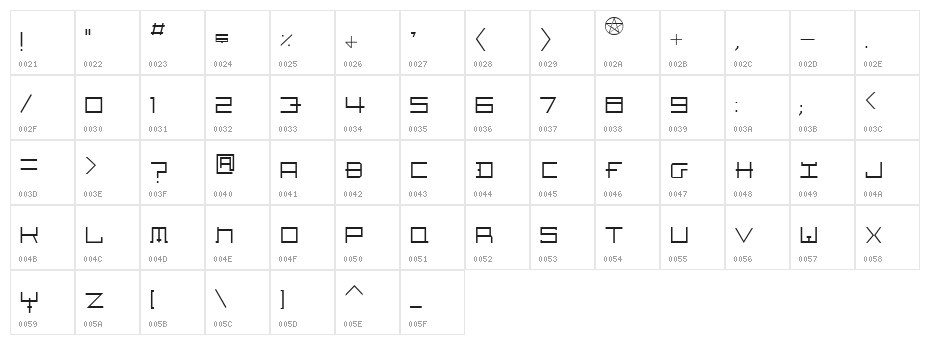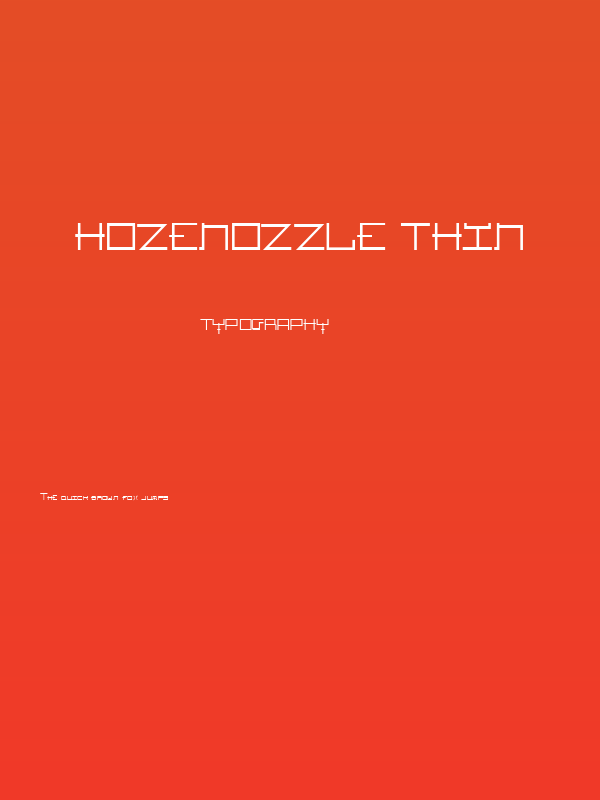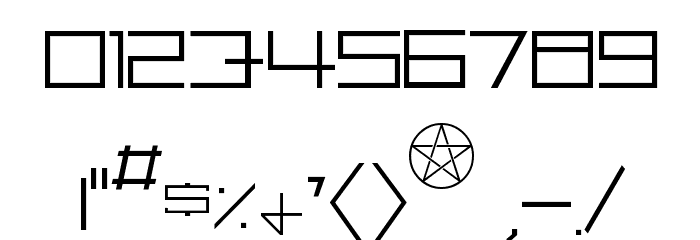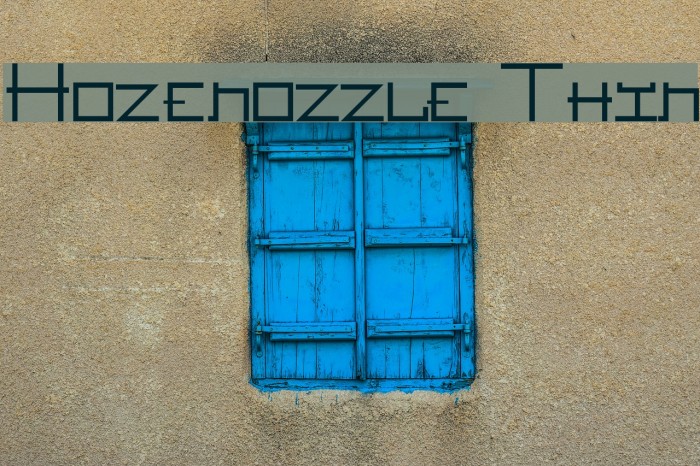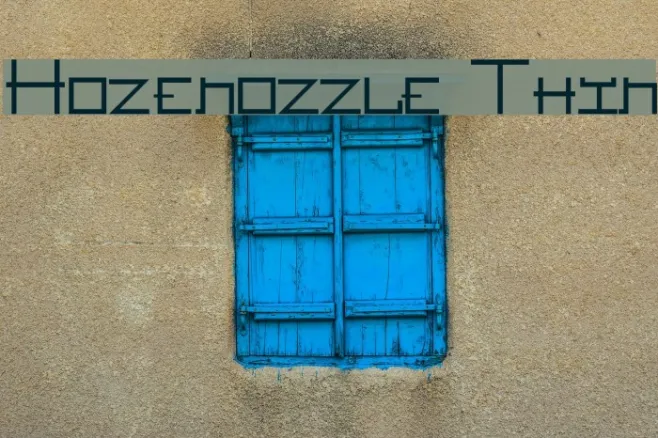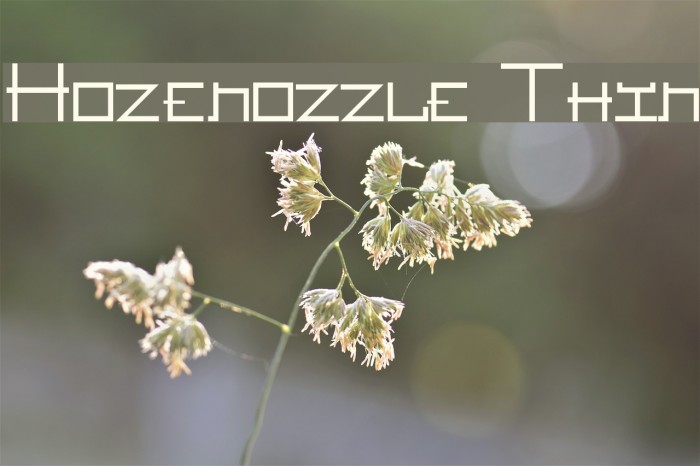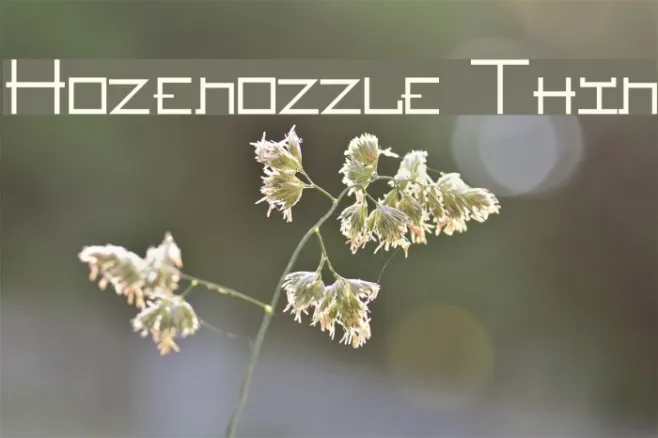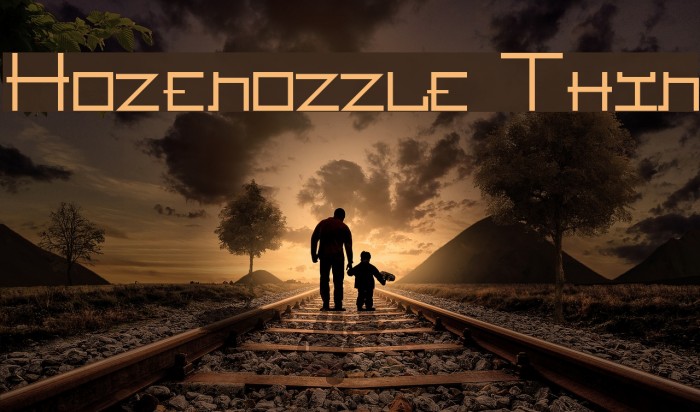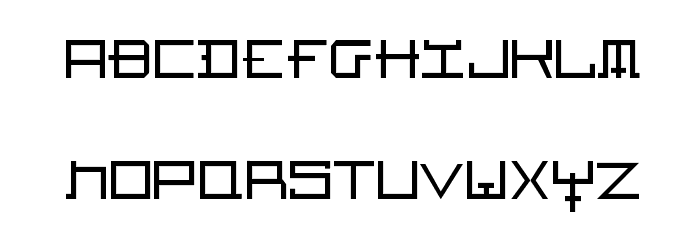
Hozenozzle Thin Font
✎ Futuristic
| Anwendungsfall | Logos, Headlines, Posters |
| Vorgeschlagene Projekte | Ideal for tech branding, digital interfaces, modern posters, and sci-fi themed designs. |